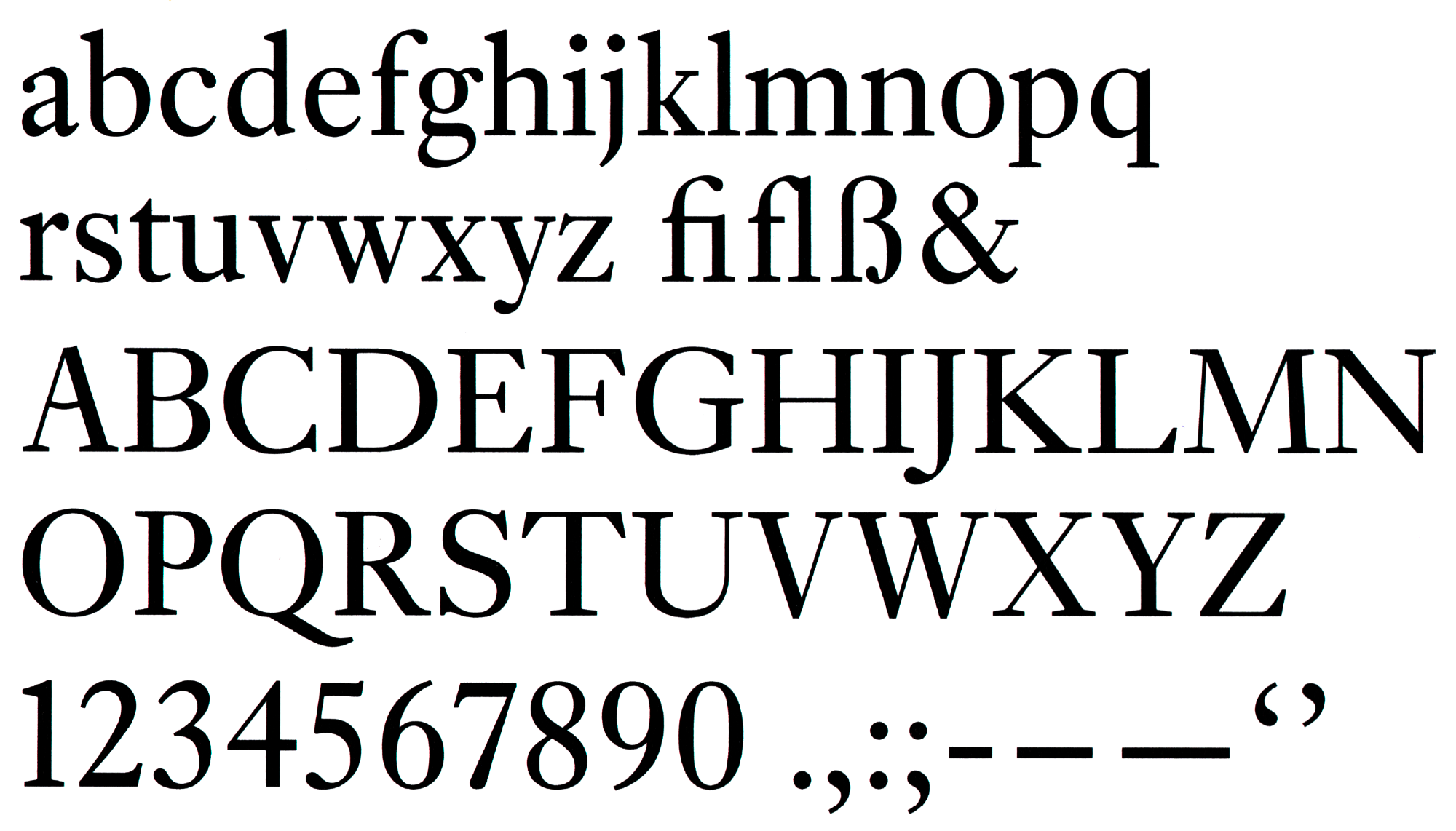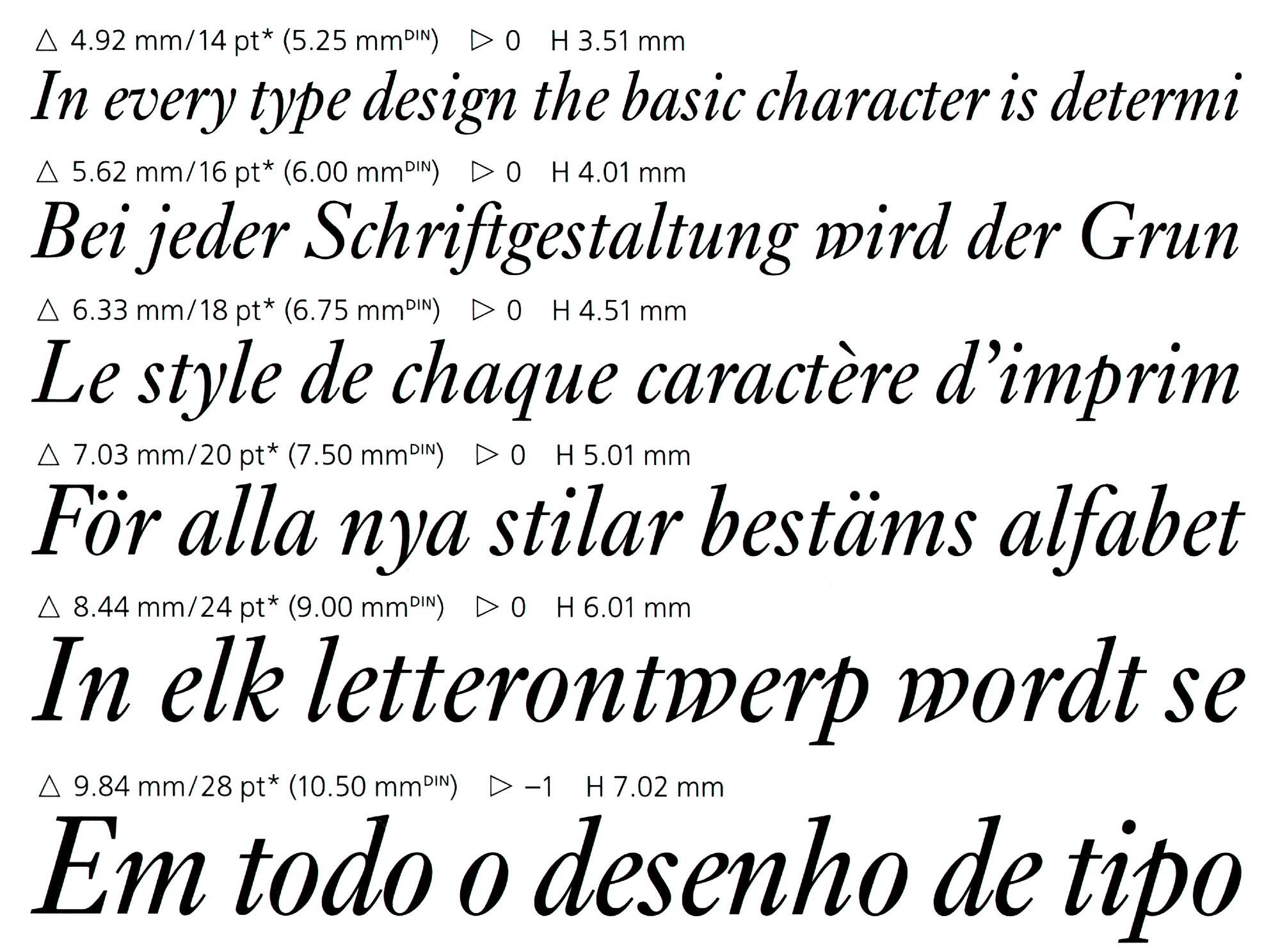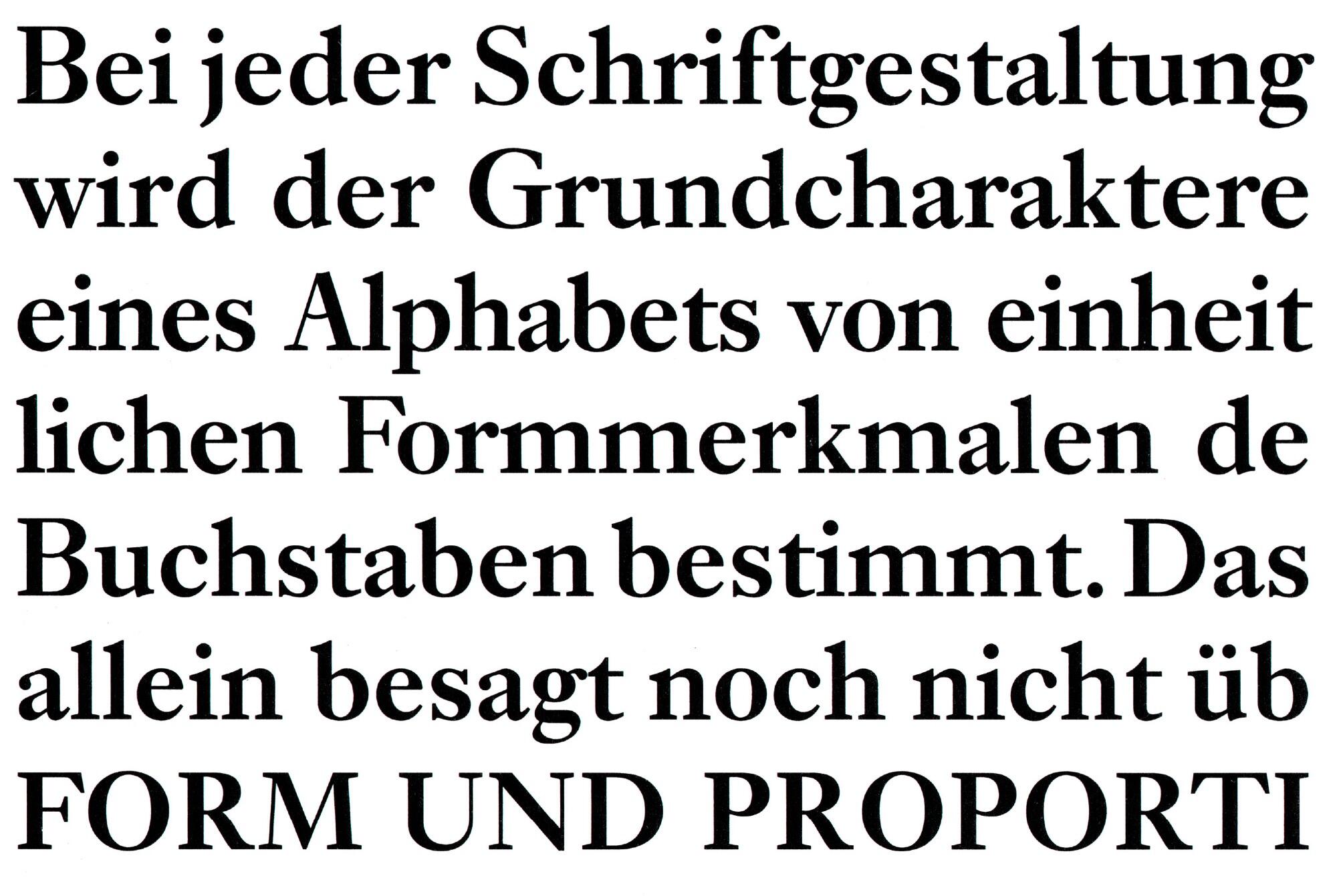
• circa 1938
• Serifen:
• serif
• Antiqua humanistisch
Die Ehrhardt ist Monotypes Bearbeitung der vor allem als Janson bekannt gewordenen Barock-Antiqua, hier jedoch benannt nach der Ehrhardtsche Gießerei in Leipzig. Die Schrift wurde bei Monotype in England entwickelt und erschien Ende den 1930er-Jahre. Zum Ausbau gehörten schlussendlich zwei Strichstärken mit Kursiven. Die Ehrhardt wurde später in den Foto- und Digitalsatz übernommen und wird heute in einer Pro-Version mit erweiterter lateinischer Belegung, Kapitälchen und mehreren Ziffernsets angeboten.